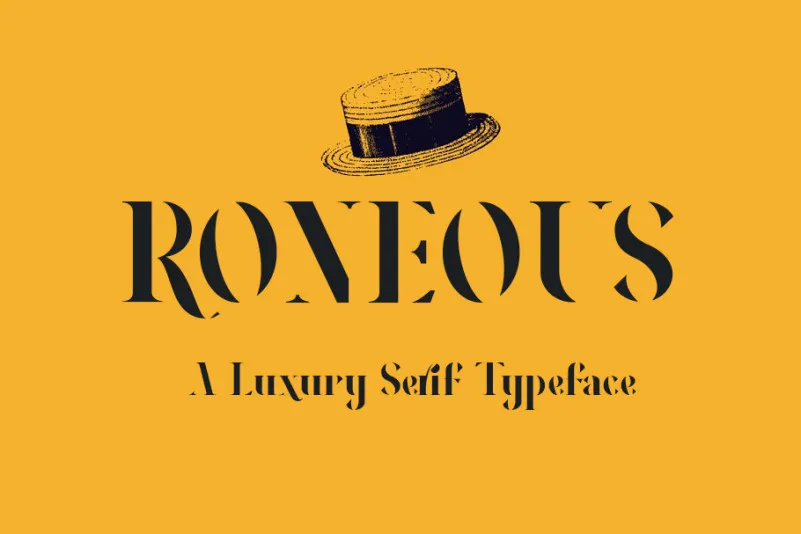
RONEOUS Serif Font – Fonte Grátis
RONEOUS Serif Font
A RONEOUS Serif é uma elegante fonte de tipo serif, com alta contraste entre as linhas que proporciona um efeito visual atraente sem comprometer a legibilidade. Feita por Gfont, esta fonte foi projetada para destacar suas características de alto contraste, cortando as linhas mais finas em seu design. Isso resulta em um tipo rico e sofisticado, perfeitamente adequado para diversos ambientes gráficos como projetos de marca, designs para casa, embalagens de produtos e cabeçalhos de revistas ou qualquer imagem de fundo que deseje adicionar um toque de elegância com uma camada de texto. Essa fonte não só enriquece o design do seu projeto, mas também adiciona uma presença visual única e moderna.
Designer: Gfont